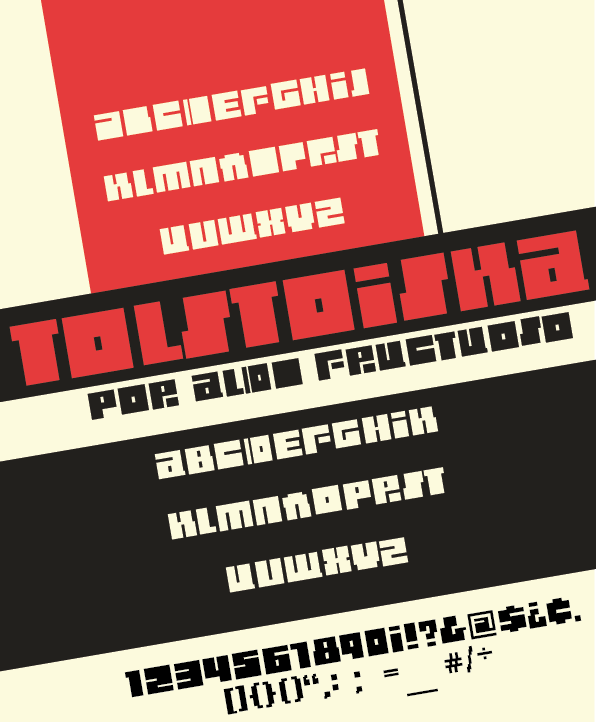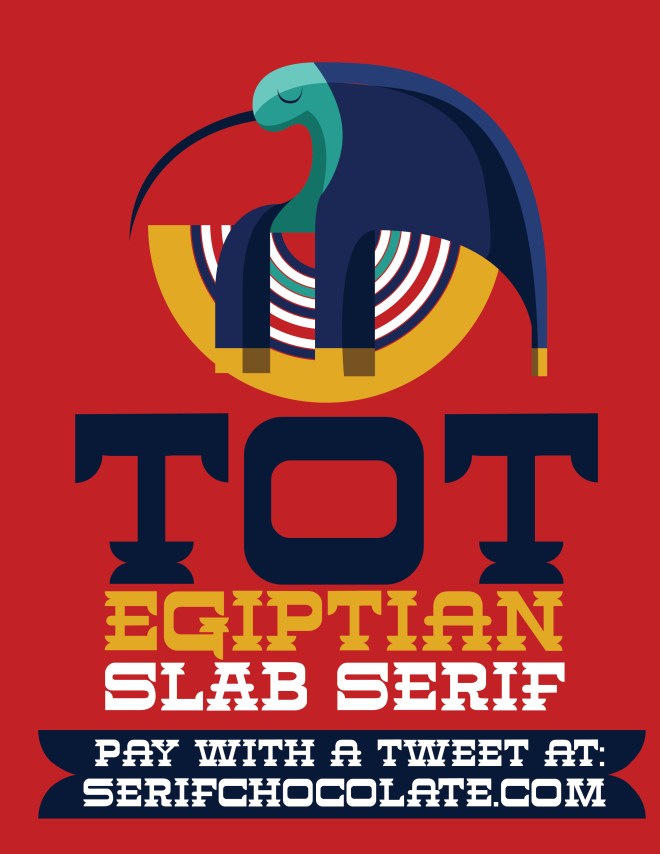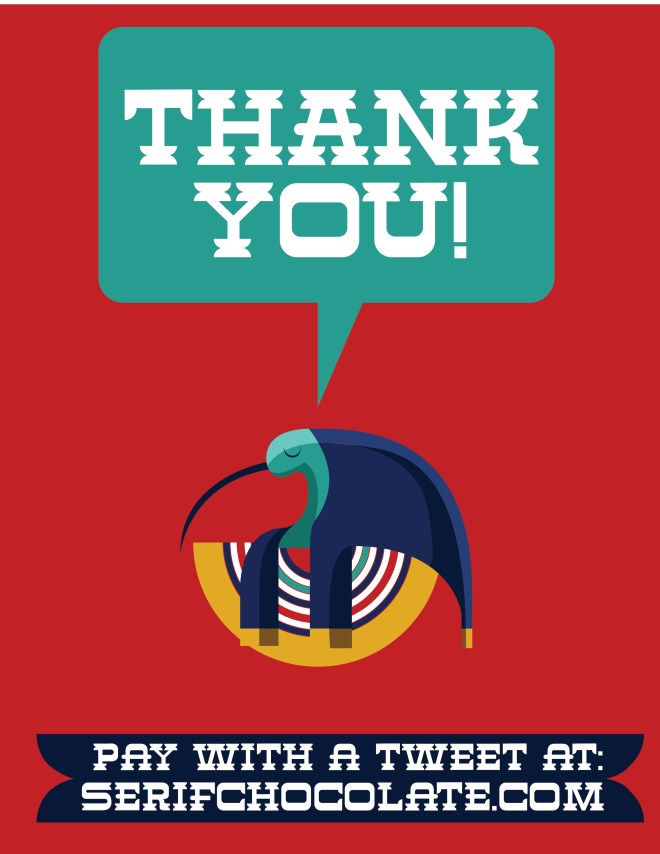
Agustina Heavy es una tipografía a medio camino entre el sentimiento de los grandes tipos de madera de la transición entre siglo XIX y XX y las curvaturas y detalles típicos de las itálicas, lo cual le da su impacto visual pero con un toque redondeado más amigable.
Fuente por un tuit: Tot
Un diseño de tipografía que recopila la fascinación del siglo XIX por el antiguo Egipto combinada con la tipografía xilográfica lo que le da un aspecto muy “western” a la vez que exótico y divertido.
A typeface design that recolects the fascination with ancient Egypt in the 19th century combined with elements of woodtype achieving a western look that is also exotic and fun.
Tipografía gratis: Vinilo
Una tipografía sans serif, bold, redondeada y con capacidad de ser aplicada como estencil, Vinilo es todo lo que una tipografía contemporánea y juvenil puede ser, ideal para carteles de fiestas en la tierra y en la playa, conciertos, exposiciones de arte urbano o o cualquier otra cosa que unas lineas curveadas que atraviesen una tipografía ultrabold redondeda puedan insinuar.
Tipografía gratis: Tolstoiska
Diseñada por el colega Aldo Fructuoso, esta tipografía inspiraba por el constructivismo ruso y los carteles soviéticos tiene una apariencia tanto vintage como moderna al tener elementos identificables con gráficas de 8bits. Y lo que es mejor esta para descargar gratis desde aquí.